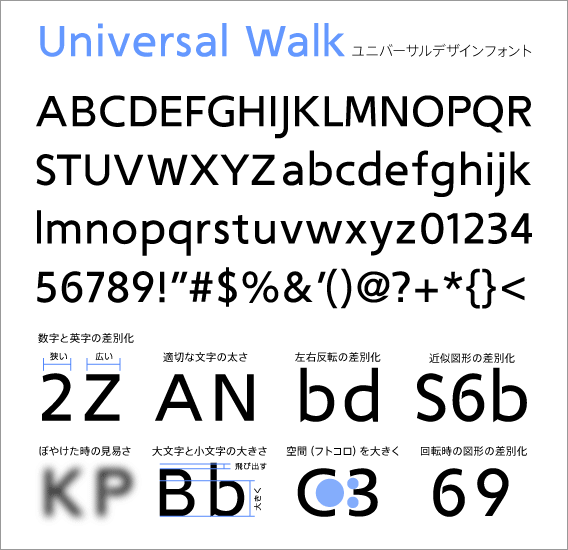
ユニバーサルウォーク
目にやさしいユニバーサルデザインのアルファベットです。ユニバーサルデザインとは、ユニバーサル=普遍的な、全体の、という言葉が示す通り、すべての人のためのデザイン。年齢や障がいの有無などにかかわらず、最初からみんなのために作られたデザインの事を言います。読みやすさ、文字の誤認識を避けるなどの工夫をすると共に、できるだけクールで格好良いフォントのデザインをと考え制作しました。それは携帯電話、家電、案内表示などは、読みやすさだけでなく格好良さも必要としているからです。親しみやすさとシャープな印象をもったフォントをお楽しみ下さい。